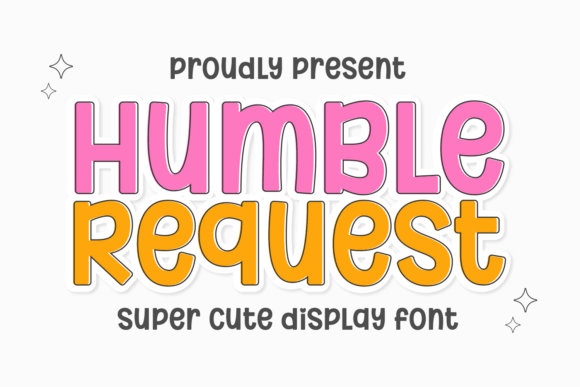
Humble Request
Поиск подходящих элементов дизайна может быть сложным, но Humble Request предлагает исключительную коллекцию, которая мгновенно улучшит вашу работу.
Создаете ли вы продукты POD (печать по требованию), свадебные приглашения или графику для социальных сетей, Humble Request станет идеальным выбором.